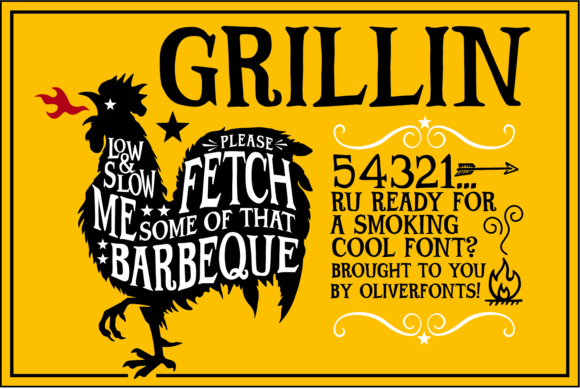
Grillin
Si buscas recursos de alta calidad como Grillin, este paquete premium es una opción fantástica para tus proyectos creativos.
Elaborado con precisión, Grillin proporciona vectores limpios, tipografía suave y una licencia comercial para tu tranquilidad.
Ya sea que estés creando productos POD (impresión bajo demanda), invitaciones de boda o gráficos para redes sociales, Grillin es una opción ideal.